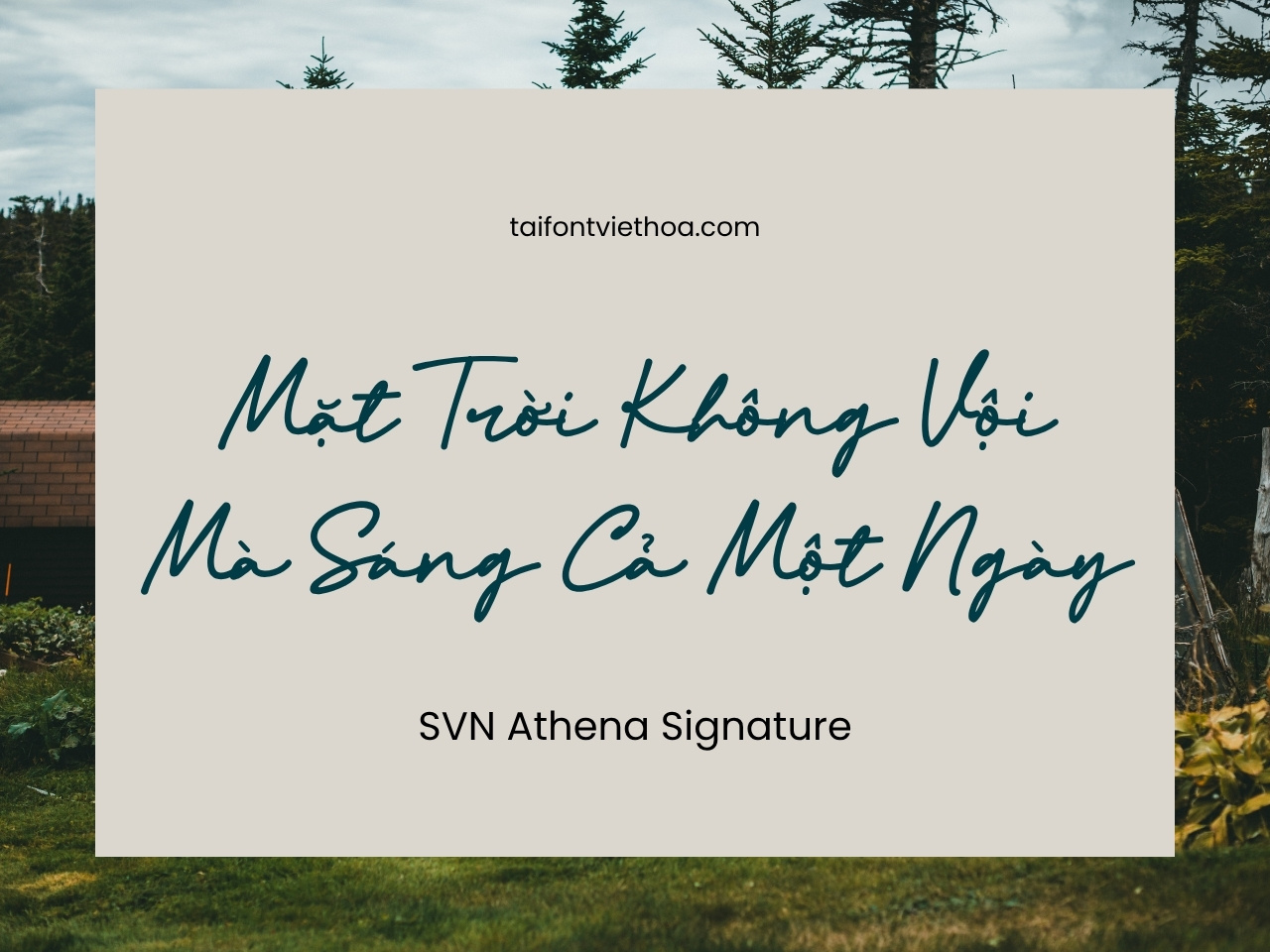
Font việt hóa SVN Athena Signature
SVN Athena Signature font chữ ký
Tác giả Font: Agam Rahmadan
Giới thiệu về font SVN Athena Signature – Kiểu chữ chữ ký viết tay mềm mại, thanh lịch và cá tính
SVN Athena Signature là phiên bản Việt hóa của font Athena Signature – một kiểu chữ chữ ký viết tay mang phong cách mềm mại, thanh lịch và rất cá tính. Font được thiết kế với các nét chữ uyển chuyển, nhẹ nhàng và tinh tế, tạo cảm giác tự nhiên và gần gũi, rất phù hợp cho các dự án thiết kế logo, chữ ký cá nhân và các sản phẩm sáng tạo cao cấp.
Phiên bản Việt hóa của SVN Athena Signature đã được Taifontviethoa.com chăm sóc kỹ lưỡng, hỗ trợ đầy đủ dấu tiếng Việt cùng hơn 60 ngôn ngữ khác. Font giúp các nhà thiết kế dễ dàng áp dụng trong nhiều dự án sáng tạo với phong cách thanh lịch, cá tính và độc đáo.
Thiết kế chữ ký viết tay – Lý tưởng cho logo cá nhân và thương hiệu cao cấp
SVN Athena Signature sở hữu các nét chữ mềm mại, bay bổng với đường nét tinh tế và hài hòa, tạo nên sự duyên dáng và chuyên nghiệp trong tổng thể thiết kế. Font rất phù hợp cho logo, chữ ký cá nhân, bao bì sản phẩm và các phần thiết kế cần điểm nhấn cá tính và sang trọng.
Ứng dụng lý tưởng: thiết kế logo cá nhân, chữ ký điện tử, bao bì mỹ phẩm cao cấp, bìa sách nghệ thuật, thiệp mời và các dự án sáng tạo cần phong cách thanh lịch, sang trọng. Ngành nghề phù hợp: thương hiệu cá nhân, mỹ phẩm, thời trang, nghệ thuật và truyền thông sáng tạo.